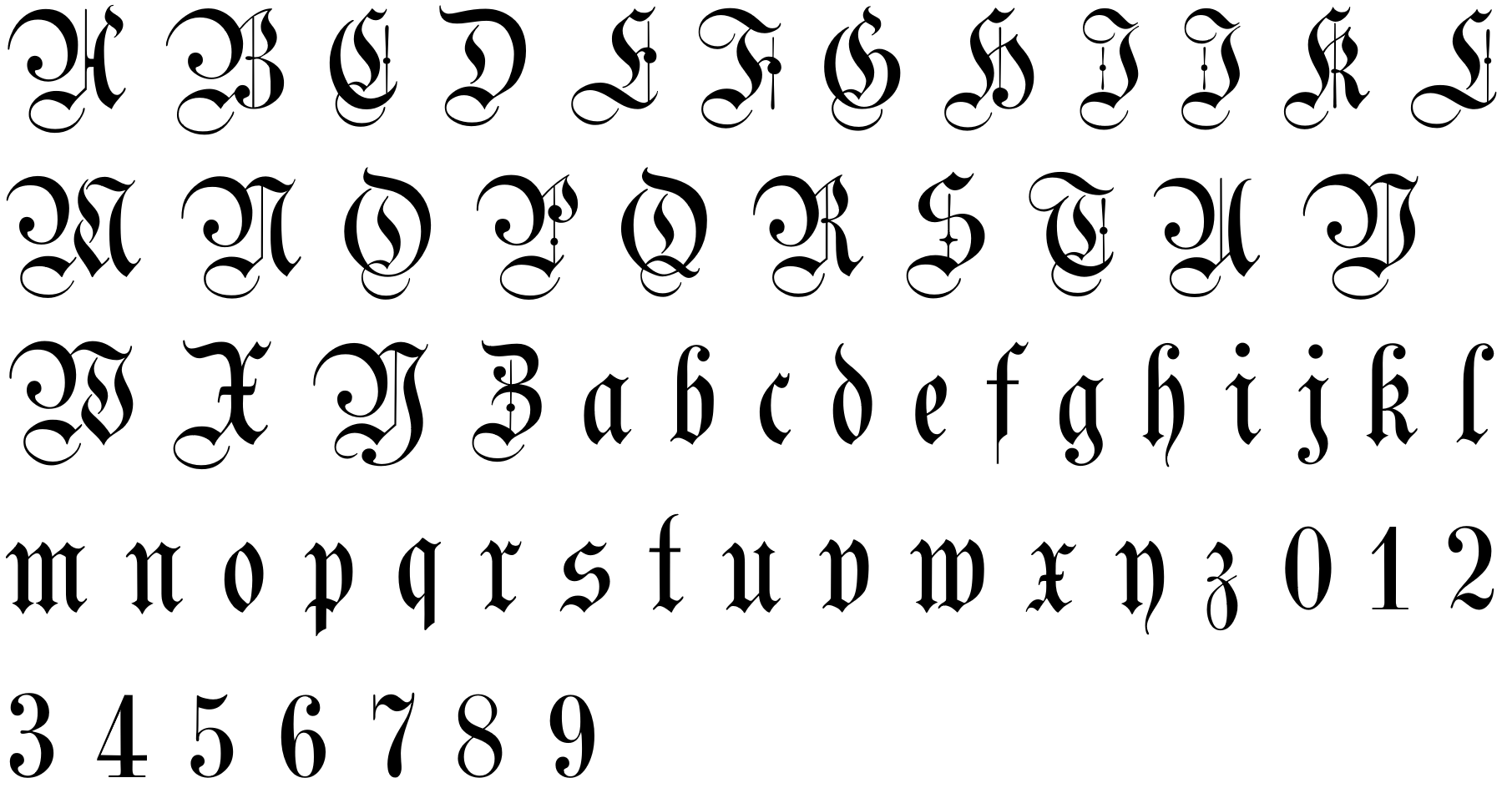
Schrift in einer alten deutsch-brasilianischen Zeitung (1860er - 1880er Jahre)
Hallo, ich arbeite mit neuronalen Netzen, um Layout-Analyse und Zeichenerkennung auf alten (um 19. und frühen 20. Jahrhundert) deutsch-brasilianischen Zeitungen zu tun, und wir sehen manchmal in einer dieser Zeitungen (nämlich "Kolonie Zeitung") diese Schriftart: https://github.com/GBN-DBP/gbn-fonts-dataset/tree/master/data/unknown
Es scheint sich um eine Art Fraktur zu handeln, aber sie ist ganz anders als die Fraktur, die hauptsächlich in unserer gesamten Basis verwendet wird (diese: https://www.pgdp.net/c/quiz/generic/images/Fraktur_alphabet.png)
Sie sieht der "Teutonic No 1" sehr ähnlich, die auf einigen Websites heruntergeladen werden kann (z.B. auf dieser:  https://es.cooltext.com/Download-Font-Teutonic+No1), aber ich frage mich, ob es eine "offizielle" Klassifizierung dafür gibt